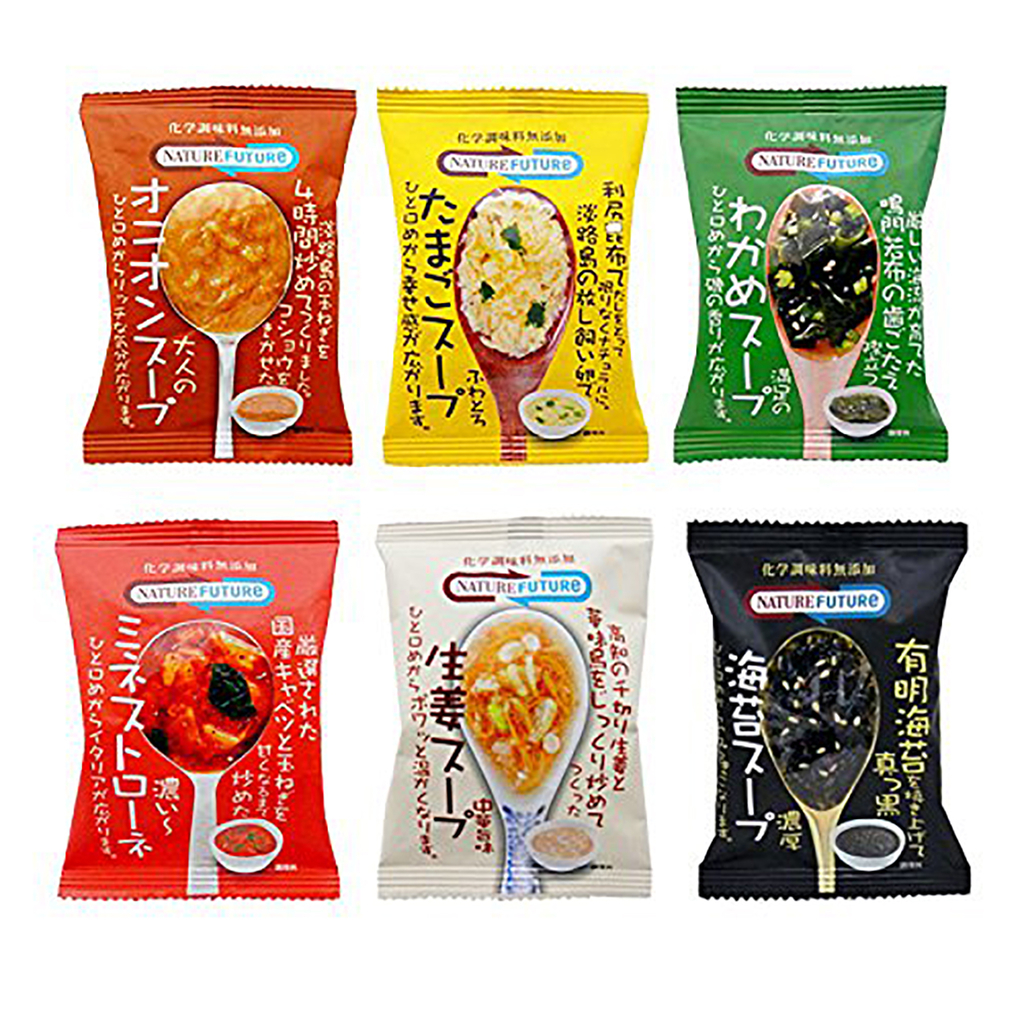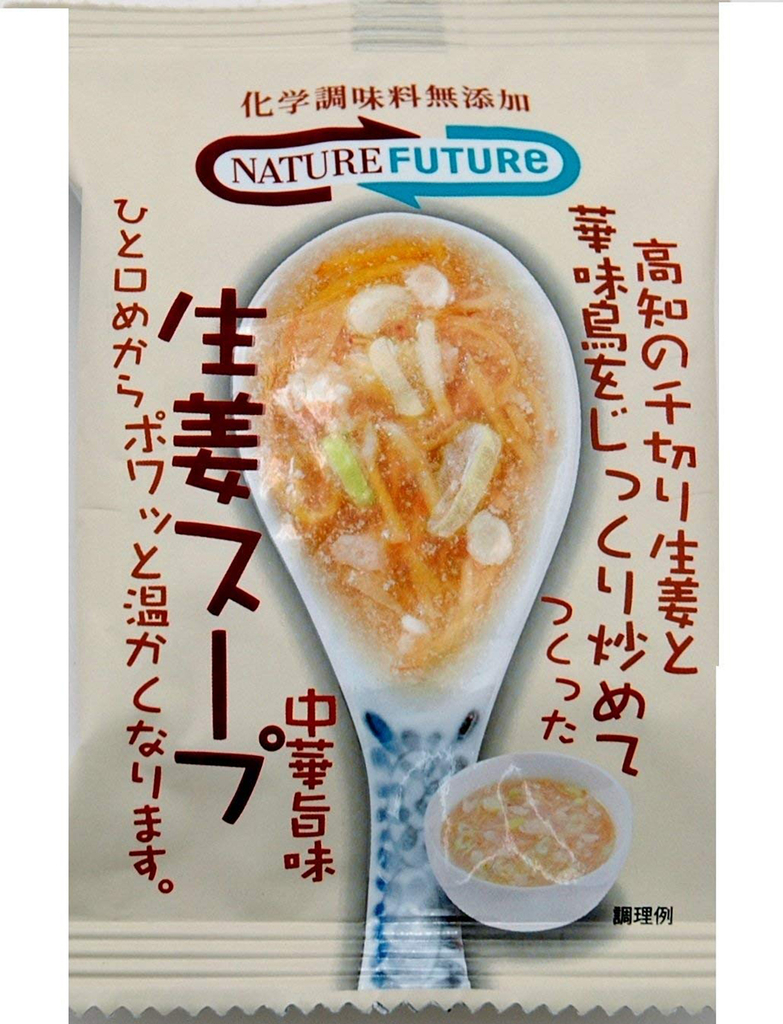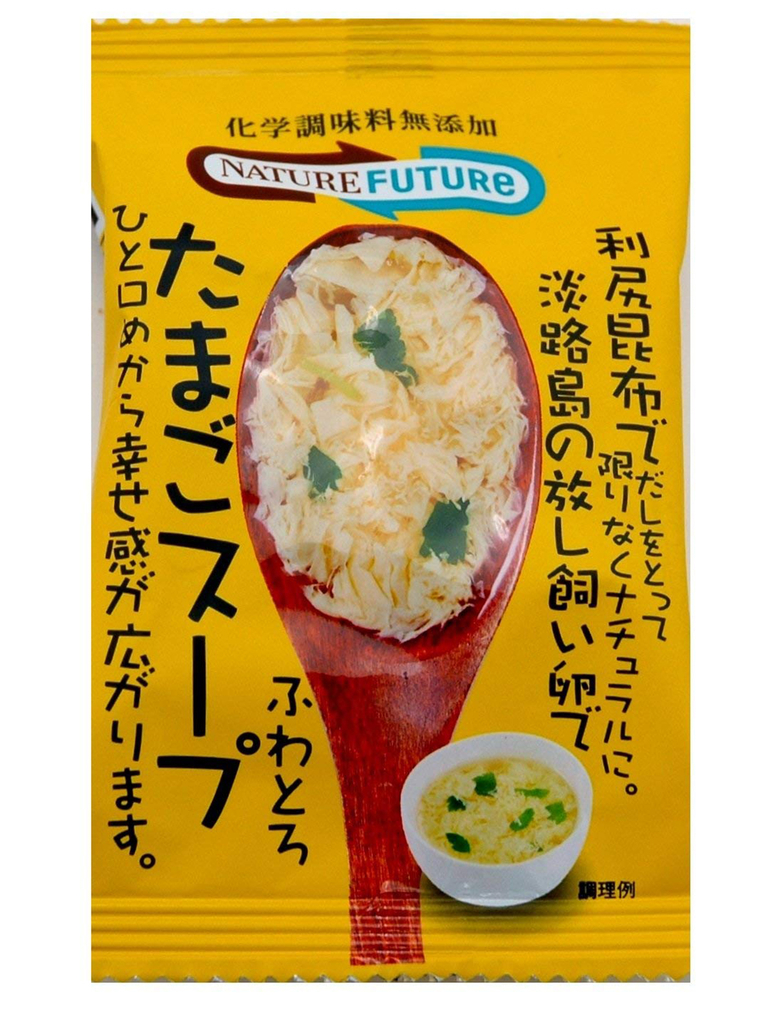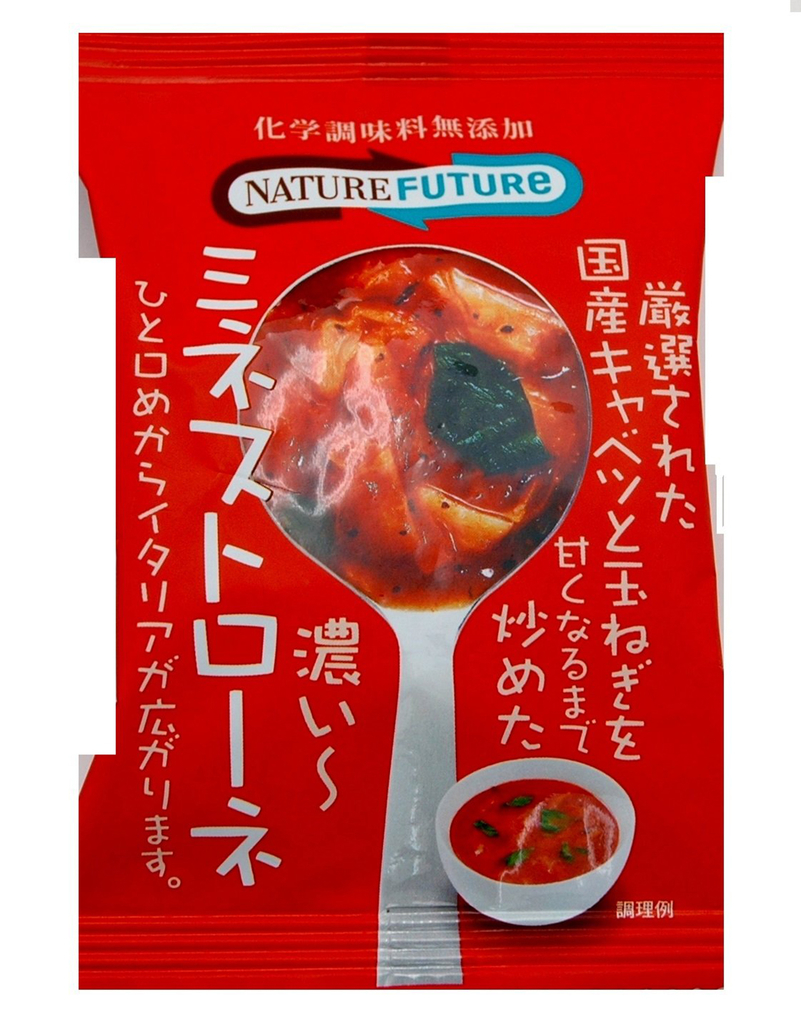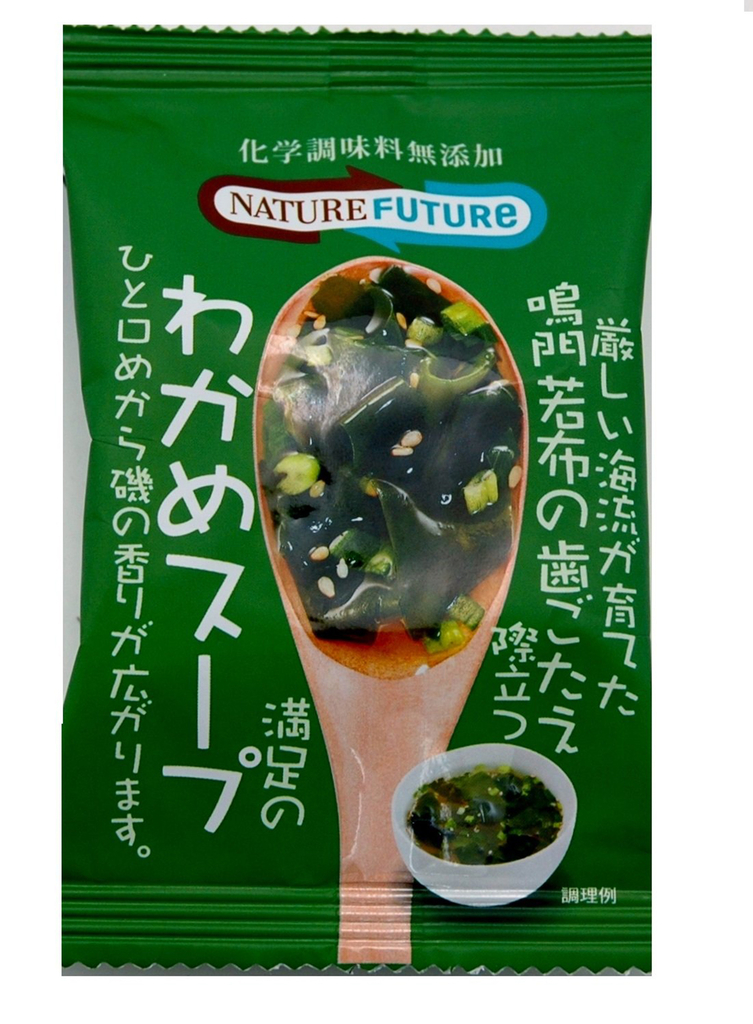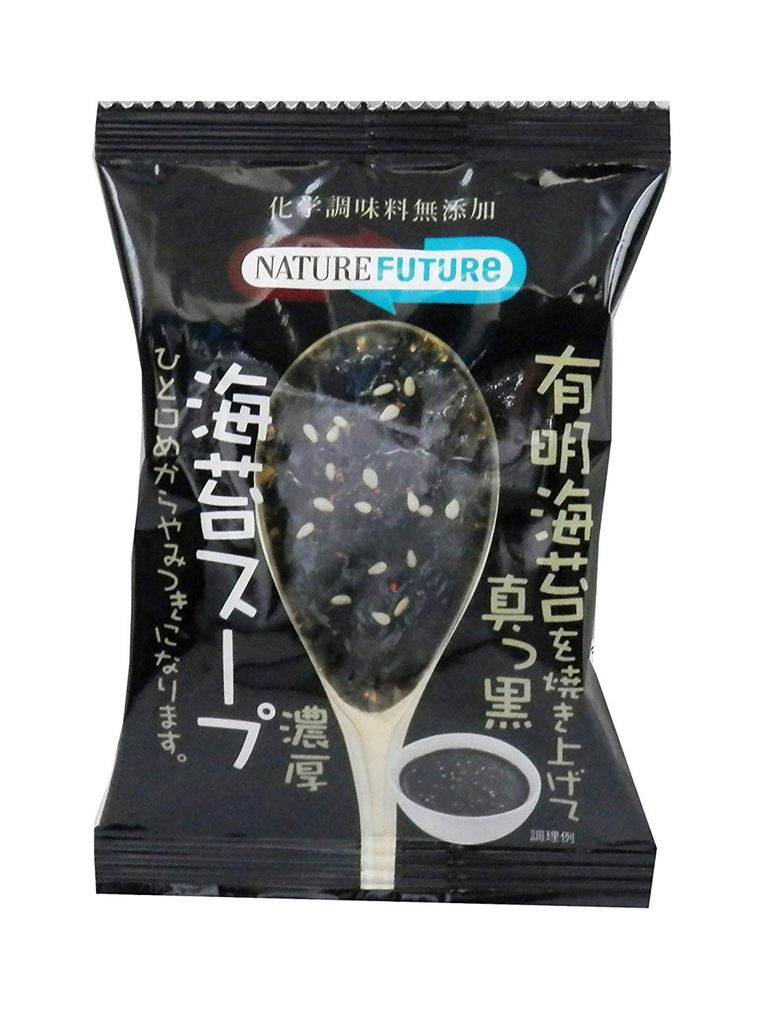
NATURE FUTURe
「NATURE FUTURe」は株式会社コスモス食品が開発・販売しているフリーズドライ製品ブランド。ブランド名は、最愛の人に届ける気持ちでモノ作りに取り組もう。あるがままの自然を大切に、おいしさに向かって誠実に歩む。というコンセプトから命名。
NATURE FUTUReスープにダイナフォントクラフト遊が採用
「NATURE FUTURe」の各スープパッケージにダイナフォントのクラフト遊が使用されている。
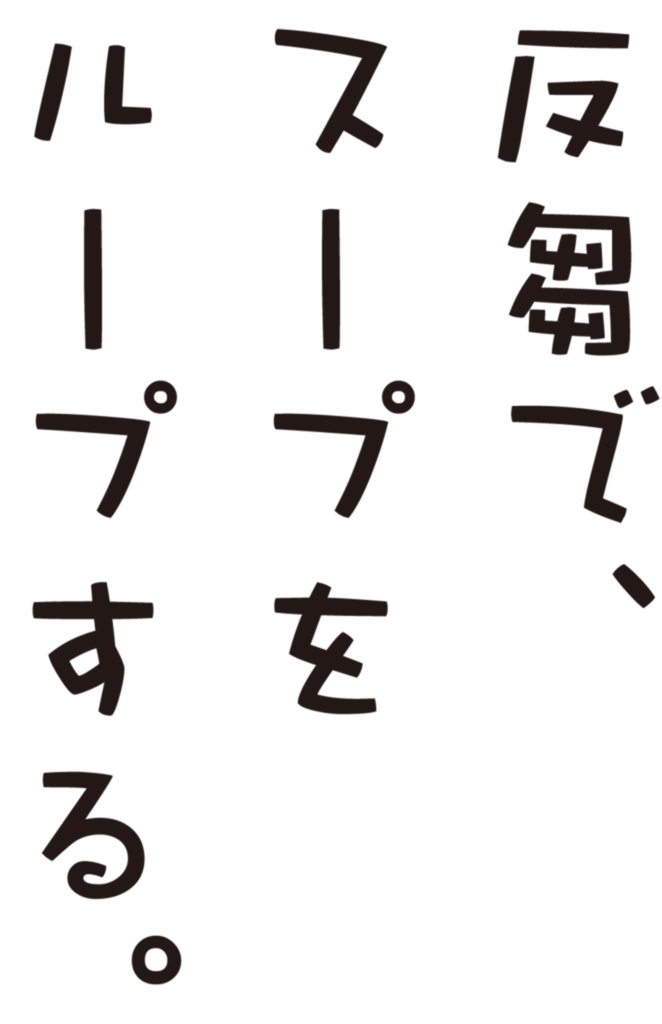
クラフト遊
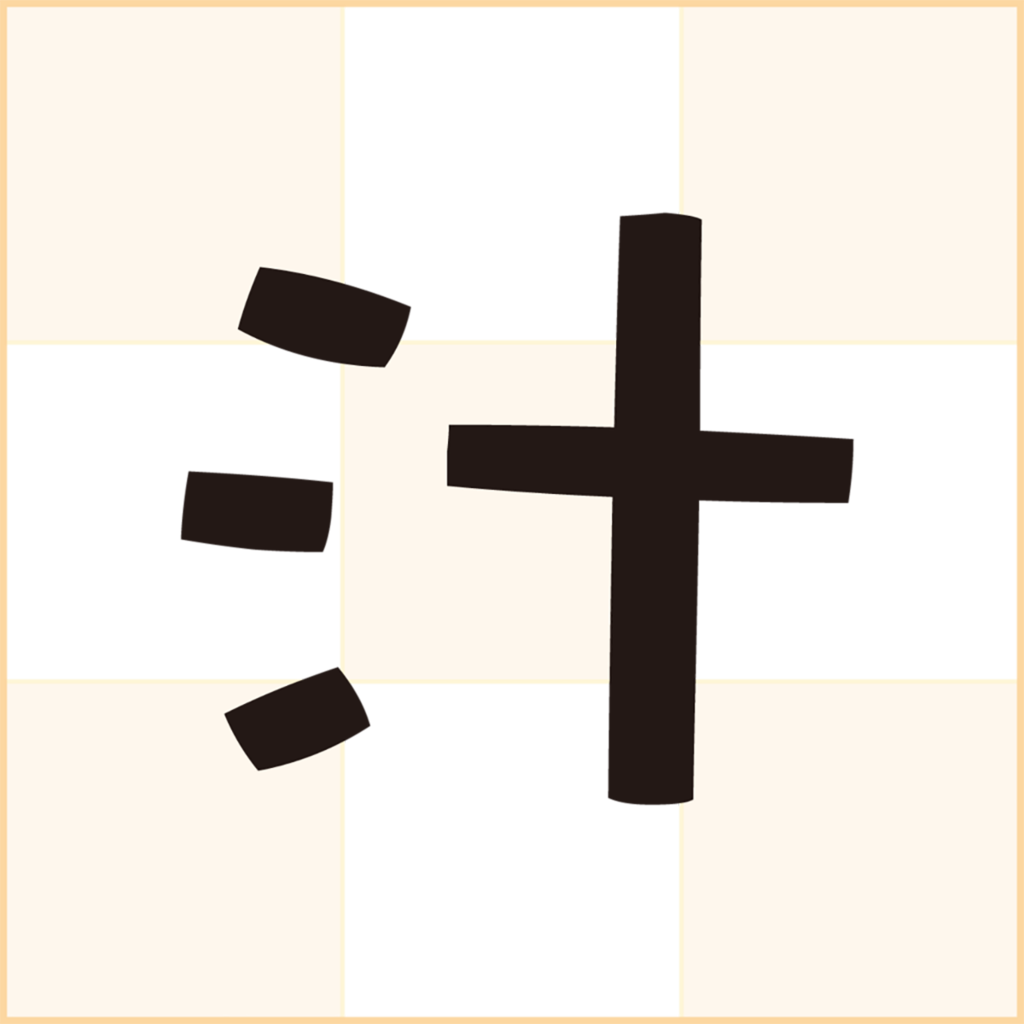
文字のユニークさや破調が表現されたかわいらしい印象の子供が書いた文字をイメージしてデザインされた書体。短い点や線で構成された字形が軽やかさを感じさせる、陽気で活発な雰囲気のデザインになっている。